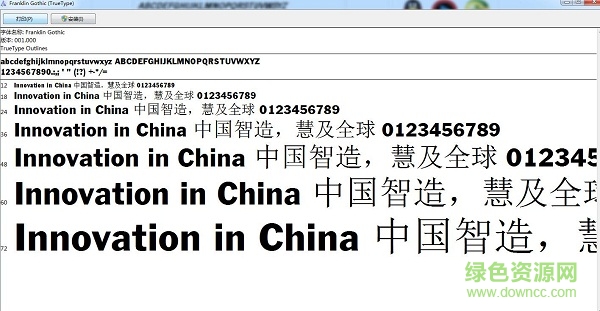
franklingothic字體是一款顯示效果非常棒的英文字體,這種類型的字體適合用在生活用品包裝設(shè)計(jì)、雜志版面、影視等領(lǐng)域,歡迎大家在綠色資源網(wǎng)免費(fèi)下載!
羅馬字母最初被雕刻到石碑上之前,要先用方頭筆刷寫好樣子,再照樣雕鑿。由于直接用方頭筆刷書寫會(huì)導(dǎo)致筆畫的起始和結(jié)尾出現(xiàn)毛糙,所以在筆畫開始、結(jié)束和轉(zhuǎn)角的時(shí)候增加了收尾的筆畫,也就自然形成了襯線。
以前稱為「黑體」或「方頭」。字體粗壯、厚實(shí)、醒目。字的筆劃粗幼,橫直相等。多用于標(biāo)題制作,有強(qiáng)調(diào)的效果,線條較幼的也可以用來排正文。